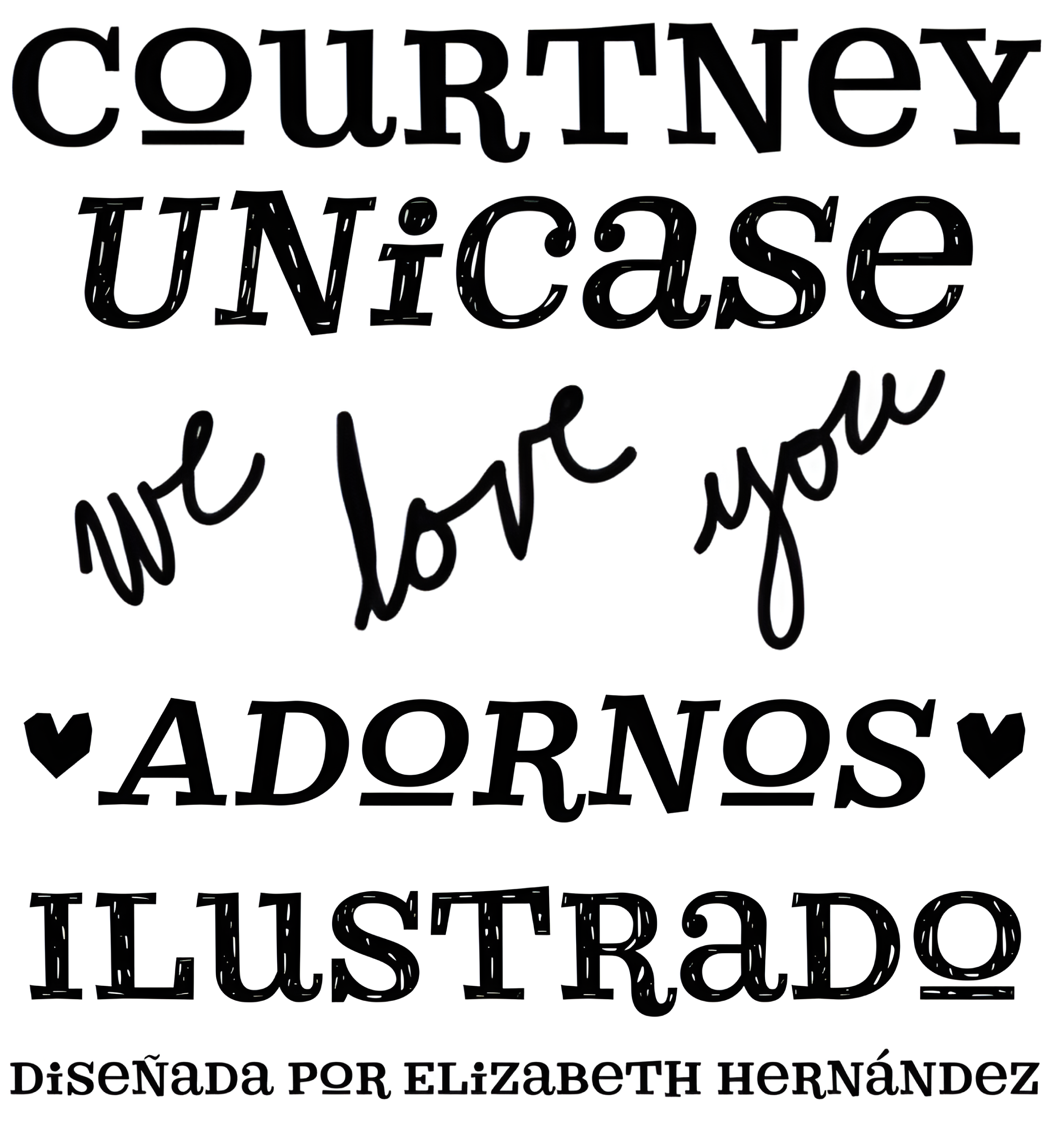
Courtney
| Año | 2013 |
| Créditos | Elizabeth Hernández |
| Descripción | Courtney es una fuente para pantalla, unicase, con trazos gruesos e irregulares. Contiene un variado conjunto de ligaduras que hacen de Courtney una fuente muy dinámica, ideal para textos breves, revistas, logotipos, etc. También posee una gran cantidad de conectores como por ejemplo: and, the, by, entre otros, diseñados para complementar la fuente. |
| Familia(s) | Courtney |
| Estilos | 4 |